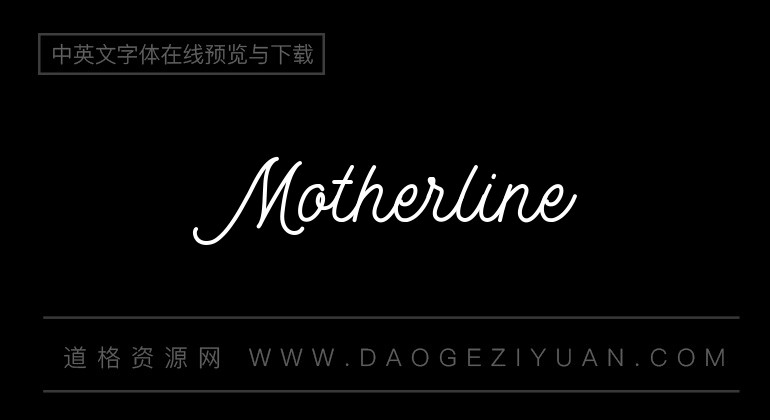
Motherline 是一款源自英国的古典字体,由英国著名的设计师 William Morris 创作。它具有细腻的线条和高雅的风格,被广泛应用于书籍、报纸、杂志、海报、商标等出版物的设计中。Motherline 的特点是它的字体结构简单,字形稳定,表现力强,可以提供清晰细腻的文字效果,从而使文字内容更加清晰明了,具有良好的可读性。内容介绍
Motherline是一款非常不错的手写艺术字体,具有很好的视觉感,适合于文化类的宣传设计、商业类品牌的广告和产品包装设计以及个性化文字排版等较多场景。